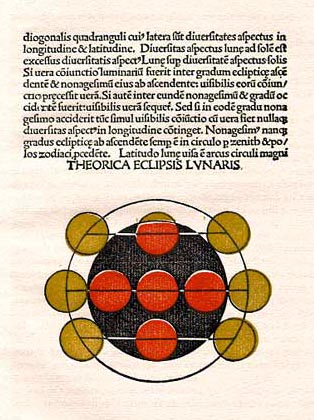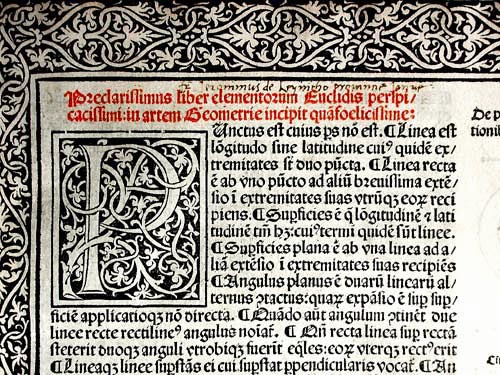
Erhardt Ratdolt (Augsburg, Veneza)O alemão Ratdolt foi um dos mestres da prototipografia, desenhador de tipos e um dos tipógrafos mais creativos nos finais do séc. XV e princípios do séc. XVI. Trabalhou em Veneza e Augsburg.
A primeira etapa profissional: de 1476 e até 1486 trabalhou em Veneza, aí imprimindo belos livros para os quais usou gravuras xilográficas e iniciais decoradas. De volta a Augsburg, imprimiu o primeiro catálogo de tipos de imprensa conhecido, no qual demonstra 15 tipos diferentes. A segunda etapa da sua carreira decorreu em Augsburg, onde imprimiu na sua oficina tipográfica obras para a Diocése de Augsburg, assim como tratados matemáticos e astronómicos.
Foi um dos primeiros impressores que não fez colorir as imagens depois da impressão, mas que as fazia imprimir num original sistema de quadricromia (negro, vermelho, amarelo e verde oliva). Necessariamente, para cada cor havia que executar uma xilogravura. Obras impressasEm 1477 Ratdolt imprimiu em Veneza a Romana historia de bellis civilibus de Appianus, e em 1482 os Elementos de Geometria de Euclides. Ratdolt especializou-se em missais, livros litúrgicos, calendários e edições sobre astronomia, astrologia e matemática. Ratdolt soube incluir nas páginas dos seus livros complexos diagramas e figuras que ilustravam os textos. Produziu igualmente a primeira folha de rosto decorada como parte integrante de um livro em 1476.
As capitulares decoradas dos seus livros (que tiveram forte influência sobre William Morris) são provavelmente o lavor de um sócio, Peter Löslein, os bordes e as ilustrações teriam sido realizadas por Bernhard Maler. Fontes digitaisRatdoldt: uma fonte OpenType, de Paulo Heitlinger BibliografiaDavid Landau and Peter Parshall. The Renaissance Print. 1995 Heitlinger, Paulo. Tipografia: origens, formas e uso das letras. Copyright © 2006 Paulo Heitlinger, ISBN 10 972-576-396-3 , ISBN 13 978-972-576-396-4, Depósito legal 248 958/06. Dinalivro. Lisboa, 2006. |